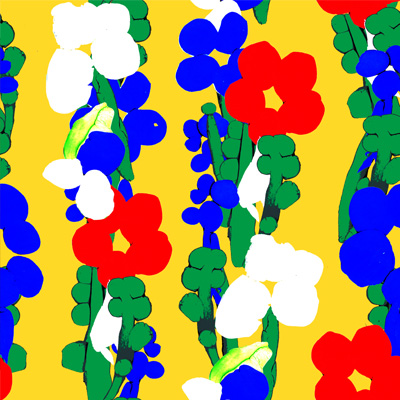
secret flower
自分だけが知っている、自分の独自の経験や個性から咲かせる花。
Artist一色栄子&東久貴
Designerユソジョ
Organizationのぞみ作業所
ふしぎな花のもようのねん土でつくりました。(一色栄子&東久貴)
描くのではなく、粘土を使った作品です。(のぞみ作業所)